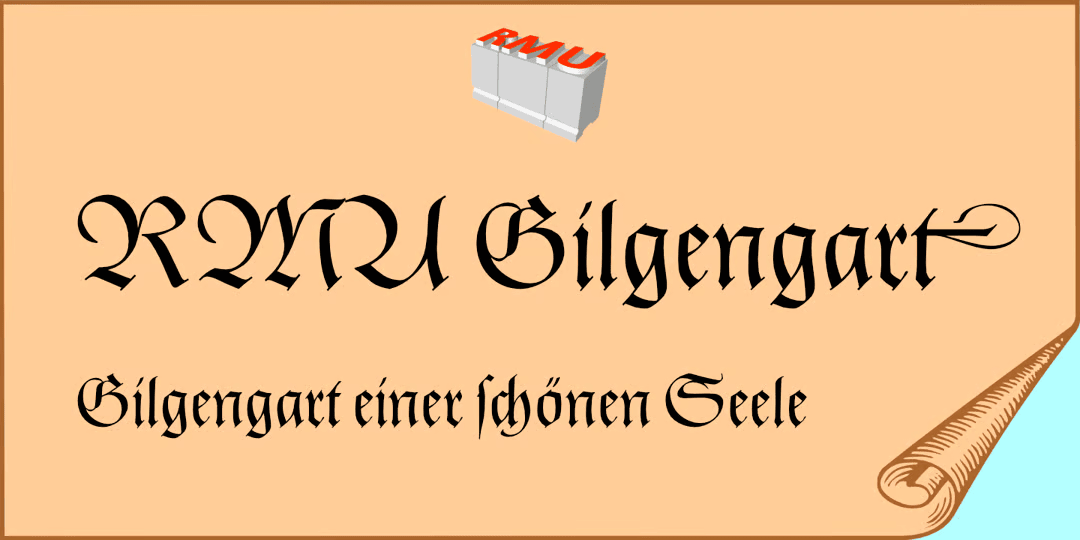
かの巨匠ヘルマン・ツァップ Hermann Zapf の知られざるマイナーなフラクトゥール。なんでこんなメジャー作家の書体が知られてないかというと、単に Linotype がデジタル化してなかったからである(笑)。元は1938年に発表された活版印刷用の書体で、どうもツァップ自身の商用タイプデザインデビュー作のようである(間違ってたらゴメン)。氏のデザインした書体は概ねデジタル化されているが、これが漏れたのは単に需要の少ないフラクトゥールだったから、かもしれない。これを古典書体の復刻を得意とする RMU がデジタル化した。カリグラフィーの名手であった氏の手腕が存分に発揮されており、フラクトゥールにしてはスッキリしていて読みやすく美しい。ちょっとしたスワッシュの付いたオルタネートもあり。ちゃんと長い s や ch のリガチャーのグリフもある。k は現代風のグリフがあっても良かったかな。